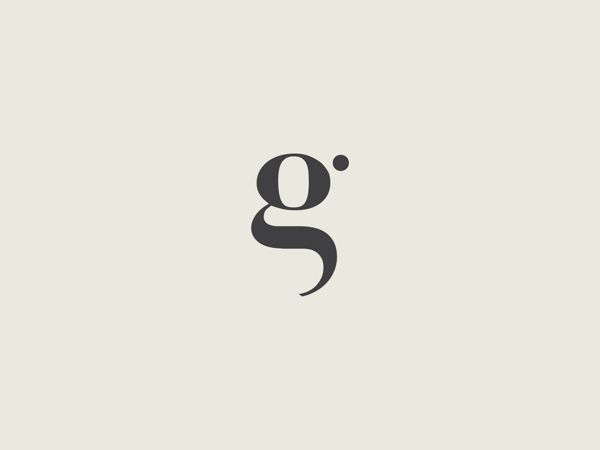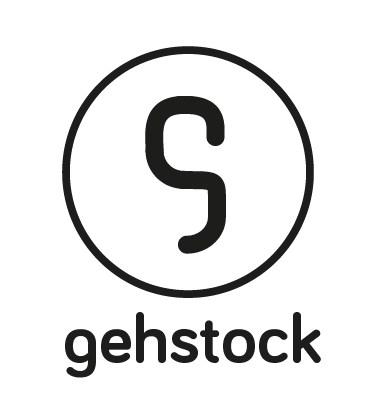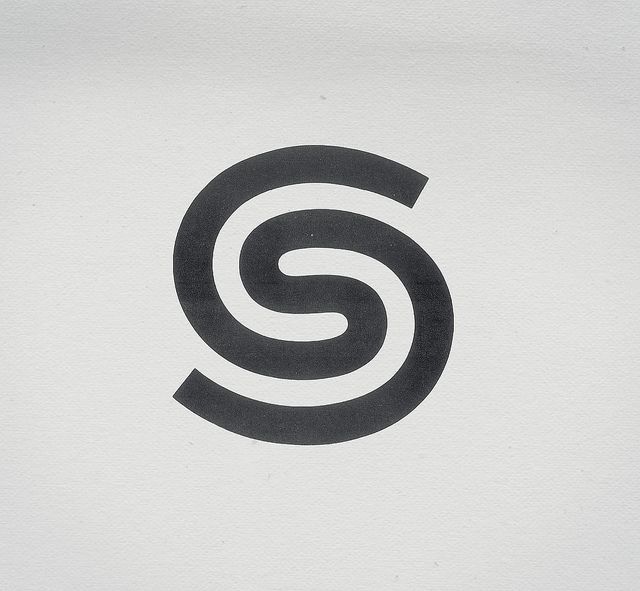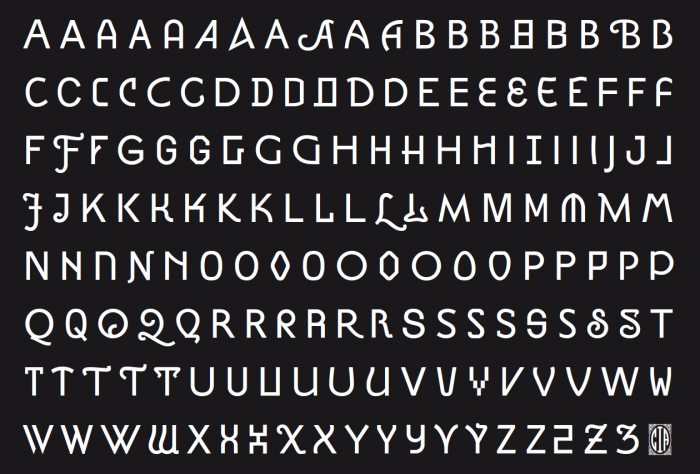
Buchstabenformvielfalt
Achso, jetzt wird mir erst einmal klar, was du konkret suchst. Ich dachte, es ginge dir um die Ausformulierung einzelner Buchstaben im Schriftkontext. Logobücher mit Monogrammen gibt es dagegen en masse.
Optimal sind diese Logobücher nicht. Manchmal entstehen die Logos aus dem Zusammenschluss zweier Buchstaben (toll!), aber manchmal ist auch noch einiges addiert worden, was nicht zum Buchstabenskelett gehört. Das hilft mir dann nicht weiter.
Die 131 finde ich zum Beispiel klasse, weil sie aufzeigt, dass ein a und g sich total ähnlich sein können. Setzt man im Entwurfprozess diese Buchstaben nebeneinander, so werden nur die besonders erfahrenen Typografen diese Gemeinsamkeit erkennen.
Die 131 finde ich zum Beispiel klasse, weil sie aufzeigt, dass ein a und g sich total ähnlich sein können.
in diesem falls sind es a, g und c — steht für 'american gas chemicals'.
Setzt man im Entwurfprozess diese Buchstaben nebeneinander, so werden nur die besonders erfahrenen Typografen diese Gemeinsamkeit erkennen.
ich glaube man das kann nicht verallgemeinern, warum nur besonders erfahrene typografen? gerade in dem oben genannten beispiel sollten das eigentlich viele erkennen.
Achso, jetzt wird mir erst einmal klar, was du konkret suchst.
Mir ist es immer noch nicht so klar. Geht es um Logos, Monogramme oder Einzelbuchstaben? Ich war davon ausgegangen, dass gegenwind eine Aufstellung von einzelnen Buchstaben verschiedener Schriften sucht. Daher hatte ich ja auf ÜberSicht verwiesen.
Ich habe mir den Ausgangsbeitrag nochmal angesehen.
Zuerst möchte ich eine Übersicht erarbeiten über alle möglichen alternativen Formskelette von Buchstaben.
Diese Übersicht soll dann ein Werkzeug werden, um schneller intelligente typographische Gemeinsamkeiten zwischen Buchstaben zu erkennen.
in diesem falls sind es a, g und c — steht für 'american gas chemicals'.
ich glaube man das kann nicht verallgemeinern, warum nur besonders erfahrene typografen? gerade in dem oben genannten beispiel sollten das eigentlich viele erkennen.
Darf ich dir ein kleines Rätsel stellen?
Hast du spontan ein Bild im Kopf von einem kleinen g, dass man auch ohne Probleme für ein s halten kann?
spontan hätte ich eine form im kopf aber ob man das ohne probleme für ein g und s hält würde ich bezweifeln. möglicherweise ist der stock ne krücke. darauf kommts aber evtl. auch nicht an, denn sofern es sich um ein logo handeln soll steht ja meistens noch was darunter was die identifizierung evtl einfacher macht, bzw. muss man die 'ligatur' auch erstmal lernen. siehe: agc – weiß ich für was es steht, fällt die erkennung einfacher.
Es gibt drei Publikationen
Norman S. Weinberger: Encyclopedia of Comparative Letterforms,, New York,1971
Christopher Perfect/Gordon Rookledge:: Rookledge's International typefinder, 1983
Kern, Michael/Koch Sieghart: ÜberSicht,Schmidt Verlag Mainz 1991
vermutlich nur antiquarisch oder in Bibliotheken zu finden.
Kern, Michael/Koch Sieghart: ÜberSicht
Das hatte ich weiter oben auch schon vorgeschlagen. :nicken:  Und auch gleich einen Link zum Verlag eingebracht, beim dem das Werk immer noch bestellt werden kann.
(Kathrin, ich konnte einfach nicht widerstehen, dich zu imitieren. Ist nicht böse gemeint. :trost: )
Norman S. Weinberger: Encyclopedia of Comparative Letterforms
in der Hoffnung, dass noch jemand etwas zu diesem Thema beitragen kann, möchte ich diesen Thread gerne nochmal Leben einhauchen.
„Rookledge's International Typefinder“ und „Compendium of Comparative Letterforms“ liegen bei mir bereits auf dem Schreibtisch.
Am ersteren Buch stört mich, dass die Formvielfalt nicht im Vordergrund steht, sondern die Identifizierung. Es sind meistens nur Nuancen zwischen den einzelnen Buchstabenskeletten vorzufinden.
Von dem zweiten Buch bin ich fasziniert, doch viele Buchstabenformen ergeben einfach nur durch kunstgeschichtliche Stile. Die Buchstaben unterscheiden sich durch ihre Dekoration, aber nicht durch ihr Formskelett.
Im Screenshot ist ein Auszug aus Jens Gehlhaar’s „Compendium Of Alphabets“ zu sehen. Die Übersicht zeigt alternative Buchstabenformen, die sich nur durch ihr Formskelett unterscheiden. Nach solchen Beispiele suche ich.